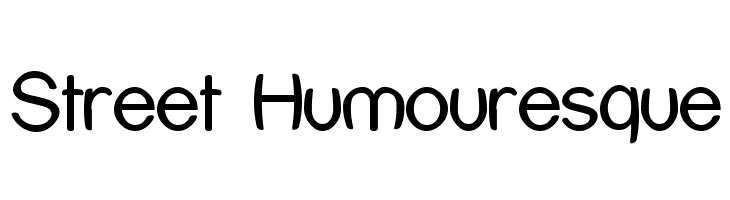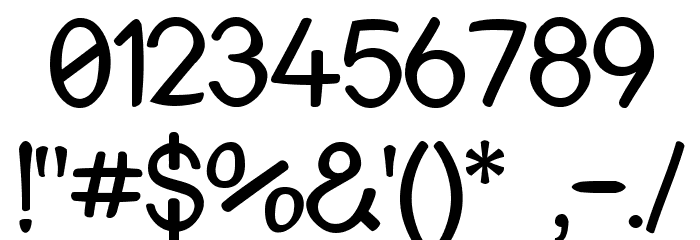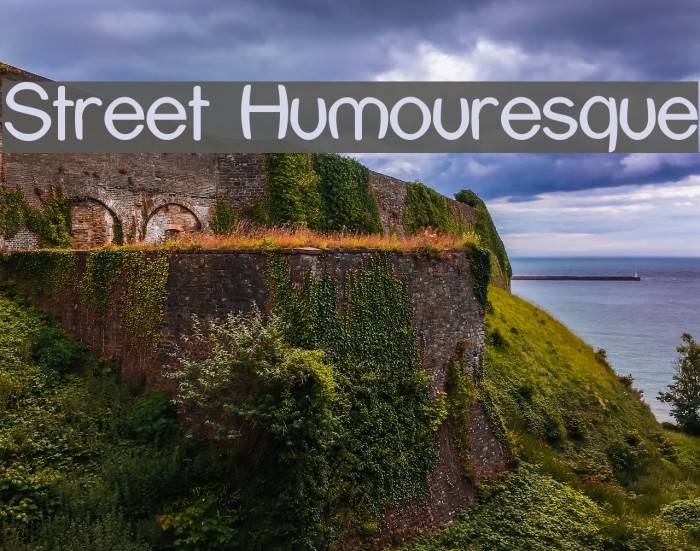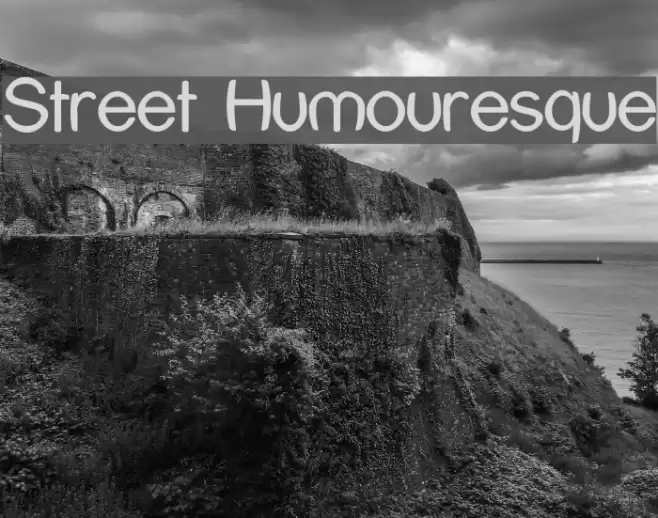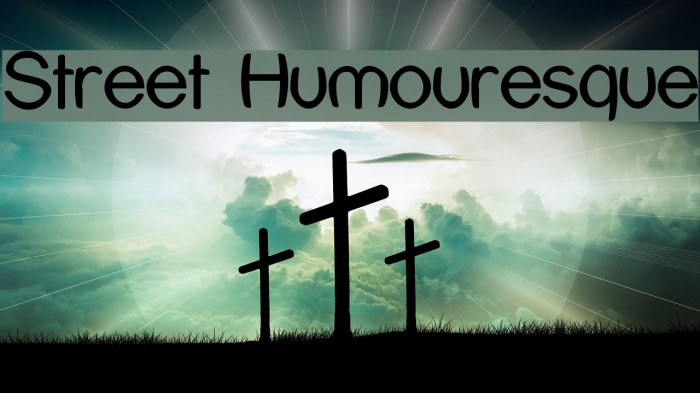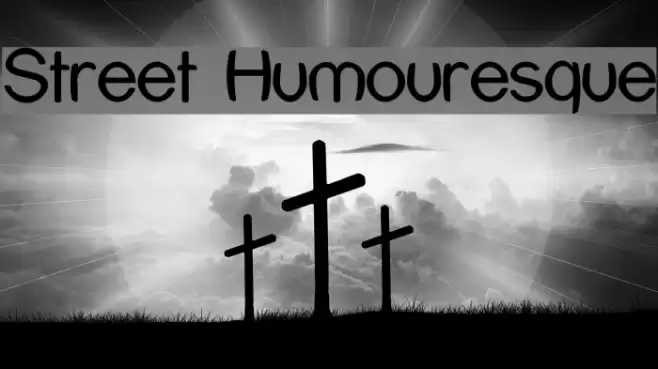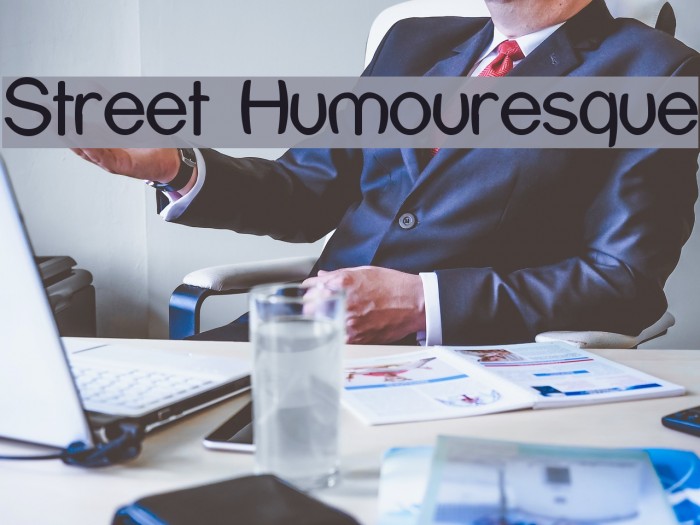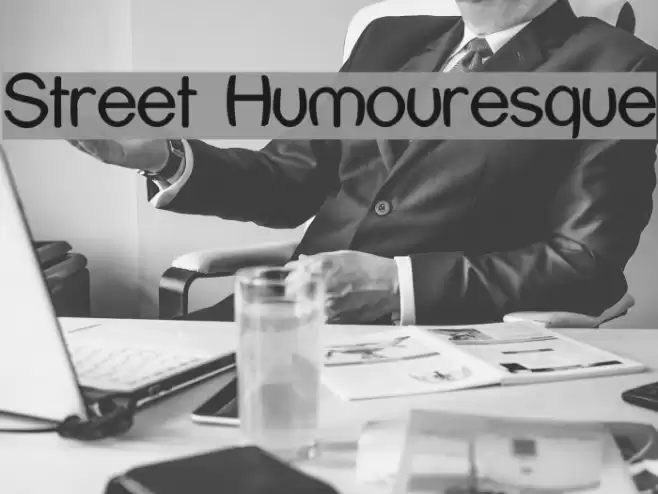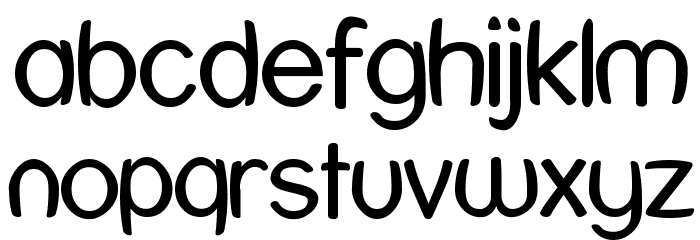
Street Humouresque Font
| Style général | Playful |
| Projets proposés | Ideal for children's books, playful branding, casual invitations, and creative posters. |
Street Humouresque